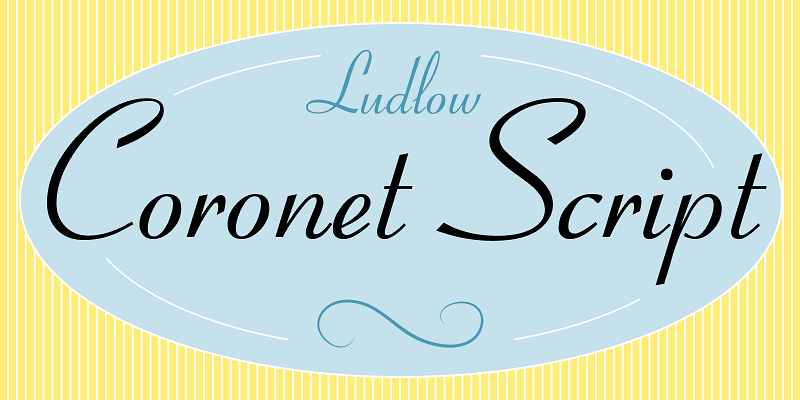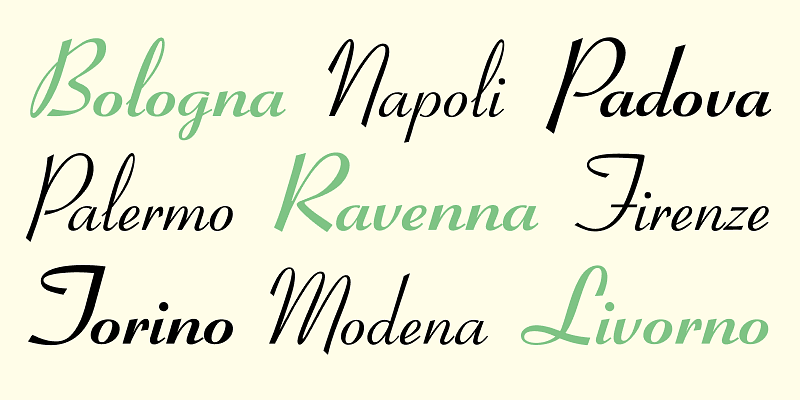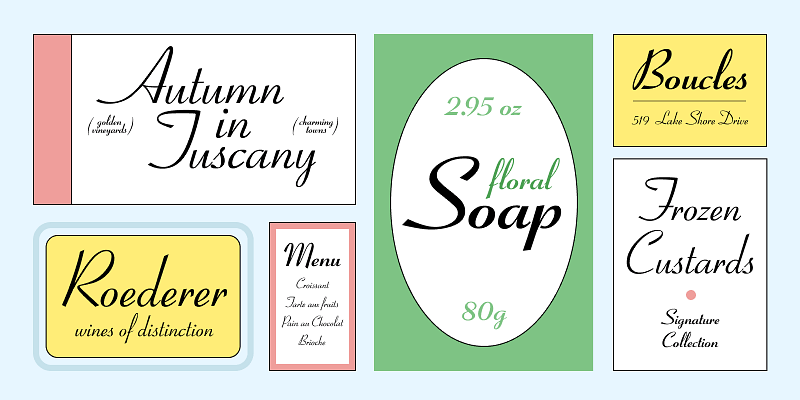
Coronet Script är ett handskriftssnitt där tecknen inte binds samman. Det designades av R. Hunter Middleton 1937 och användes med Ludlow Typograph. Versalerna är stora gester med svepande kurvor, och gemenerna är kompakta och fulla av rörelse. Tillsammans skapar de ordformer som passar skivomslag, modemärken, mediemärken, skyddsomslag till böcker och filmtitlar.
Ludlow Typefaces är en rad teckensnitt i handstils-, seriff- och sanserifformat för accidens- och textbruk. De flesta av de mer populära snitten formgavs av den berömda formgivaren R. Hunter Middleton. Den aktiva produktionslivslängden för Ludlow Typograph varade i drygt 80 år. Eftersom det var en maskin för handsättning användes den främst för uppseendeväckande rubriker. På det viset var den en trendsättare. Dessa fantastiska fonter har uppdaterats från originalen och för dagens typografiska behov.